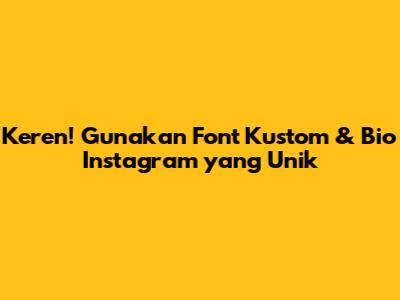
- Buka font generator: Cari di Google dengan kata kunci seperti "font Instagram", "font generator", atau "n0oscfontsc generator".
- Ketik teks: Ketik teks yang ingin kamu gunakan di bio Instagram kamu pada kolom yang disediakan.
- Pilih font: Pilih font yang paling kamu suka dari daftar pilihan yang tersedia.
- Salin dan tempel: Salin teks dengan font kustom yang sudah kamu pilih, lalu tempelkan di bio Instagram kamu.
- Cool Fonts: Salah satu website populer yang menyediakan berbagai macam font kustom untuk Instagram dan platform lainnya. Tampilannya sederhana dan mudah digunakan.
- LingoJam: Menyediakan banyak pilihan font yang unik dan menarik. Kamu bisa langsung mengetik teks dan melihat hasilnya.
- Instagram Fonts: Website khusus yang fokus pada font untuk Instagram. Menyediakan berbagai macam font dengan tampilan yang berbeda-beda.
- Font: Font yang elegan dan stylish.
- Bio:
Fashion Enthusiast | Sharing Style Tips & Inspiration โจ โก๏ธ Website Link ๐ Contact for Collabs
- Font: Font yang unik dan adventurous.
- Bio:
Wanderlust & Adventure Seeker โ๏ธ Exploring the World | Sharing Travel Stories ๐๐ Location โก๏ธ Link to Blog
- Font: Font yang menarik perhatian dan eye-catching.
- Bio:
๐๏ธ Online Shop Shop Now for Latest Collection! ๐ โก๏ธ Link to Shop ๐ Free Shipping
Mau bio Instagram kamu makin kece dan beda dari yang lain, guys? Pengen profil Instagram kamu langsung menarik perhatian dan bikin orang penasaran? Nah, kamu datang ke tempat yang tepat! Artikel ini bakal ngebahas tuntas tentang n0oscfontsc, font-font keren, dan cara bikin bio Instagram yang gak cuma informatif tapi juga stylish abis. Jadi, siap-siap buat merombak tampilan Instagram kamu jadi lebih menarik dan punya ciri khas!
Kenapa Font Kustom Penting untuk Bio Instagram?
Guys, pernah gak sih scroll Instagram dan langsung tertarik sama profil yang tampilannya beda? Nah, salah satu kunci utama dari tampilan yang unik adalah penggunaan font kustom. Di dunia yang serba visual kayak Instagram, font bukan cuma sekadar tulisan, tapi juga bagian dari branding diri atau brand kamu. Dengan font yang tepat, kamu bisa menyampaikan pesan, kepribadian, dan gaya kamu dengan lebih efektif.
Meningkatkan Daya Tarik Visual
Bayangin aja, bio Instagram kamu cuma pakai font standar yang itu-itu aja. Kelihatan kurang menarik, kan? Font kustom memberikan sentuhan visual yang segar dan beda. Ini kayak kamu pakai baju yang stylish di antara orang-orang yang pakai baju biasa. It's all about standing out, right?
Menunjukkan Kreativitas dan Personalitas
Penggunaan font kustom juga nunjukkin kalau kamu kreatif dan punya selera yang unik. Kamu bisa memilih font yang sesuai dengan niche atau gaya hidup kamu. Misalnya, kalau kamu suka hal-hal yang vintage, kamu bisa pakai font yang klasik. Kalau kamu anak milenial yang funky, kamu bisa pilih font yang modern dan berani.
Membangun Brand Identity
Buat kamu yang punya bisnis atau brand di Instagram, font kustom itu penting banget buat membangun brand identity. Font yang konsisten akan membantu orang-orang mengenali brand kamu dengan lebih mudah. Ketika orang melihat font yang sama di setiap postingan atau bio Instagram kamu, mereka akan langsung teringat dengan brand kamu.
Apa Itu n0oscfontsc dan Bagaimana Cara Menggunakannya?
n0oscfontsc itu apa sih, dan gimana cara pakainya? Sederhananya, ini adalah istilah yang sering digunakan untuk merujuk pada font-font keren yang bisa kamu pakai di Instagram. Ada banyak sekali pilihan font yang bisa kamu gunakan, mulai dari yang sederhana sampai yang rumit.
Cara Mendapatkan Font Kustom
Gimana caranya dapetin font-font keren ini? Kamu bisa menggunakan beberapa tools atau website yang menyediakan layanan font generator untuk Instagram. Caranya gampang banget:
Gampang banget, kan?
Contoh Beberapa Website Font Generator
Tips Membuat Bio Instagram yang Menarik
Selain font kustom, ada beberapa tips lain yang bisa kamu terapkan untuk membuat bio Instagram kamu makin menarik:
Gunakan Emoji
Emoji bisa bikin bio Instagram kamu lebih hidup dan ekspresif. Gunakan emoji yang relevan dengan konten atau kepribadian kamu. Jangan berlebihan, tapi cukup tambahkan beberapa emoji untuk mempercantik tampilan bio kamu.
Buat Deskripsi yang Singkat dan Jelas
Orang-orang biasanya cuma punya waktu beberapa detik untuk melihat bio Instagram kamu. Jadi, pastikan deskripsi kamu singkat, padat, dan jelas. Jelaskan siapa kamu, apa yang kamu lakukan, atau apa yang bisa orang lain dapatkan dari kamu.
Tambahkan Call to Action
Jangan lupa tambahkan call to action (CTA) di bio kamu. Ajak orang-orang untuk melakukan sesuatu, misalnya mengunjungi website kamu, menghubungi kamu, atau mengikuti akun kamu. CTA bisa berupa kalimat seperti "Kunjungi website kami", "Hubungi kami sekarang", atau "Follow akun kami".